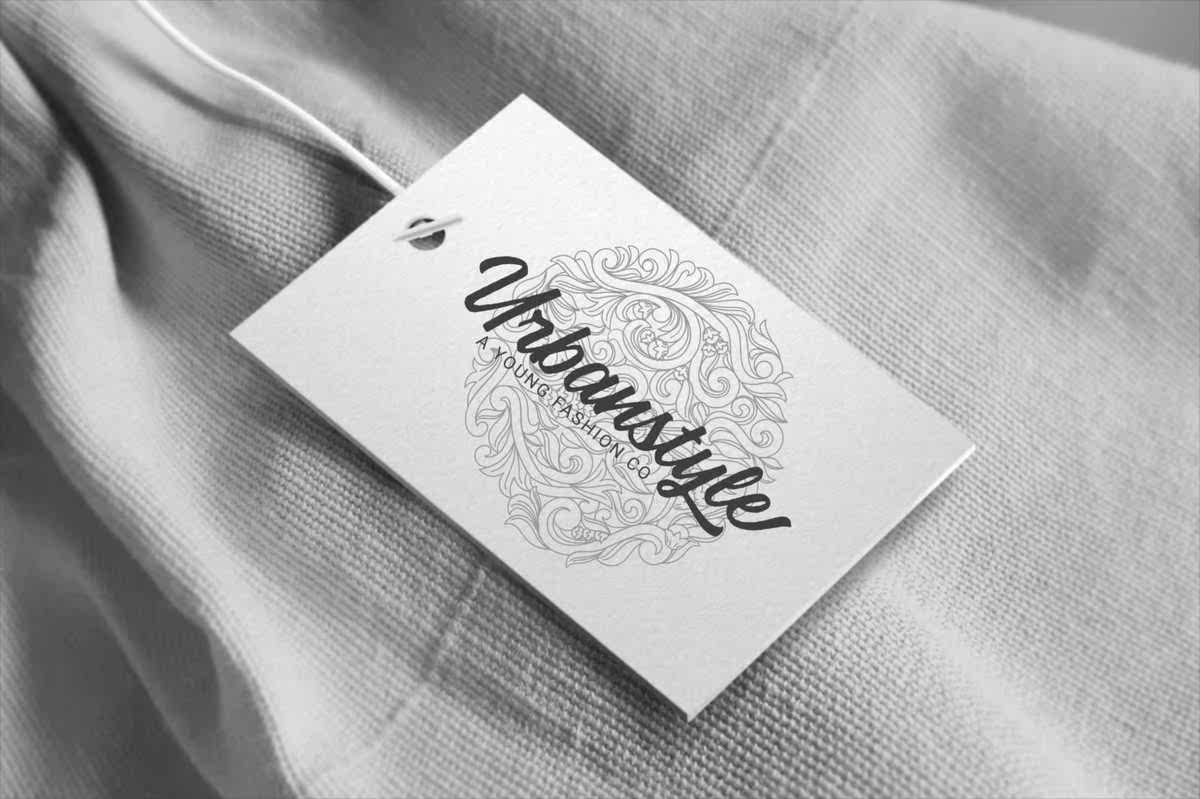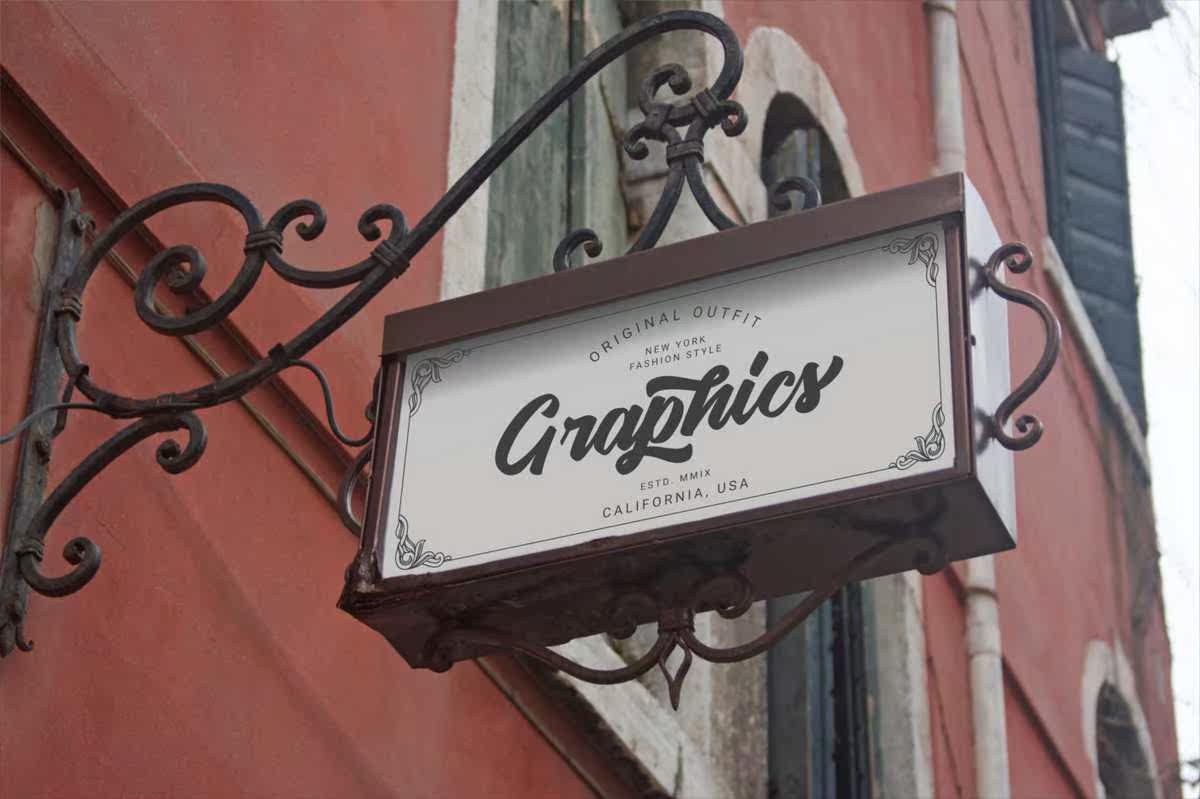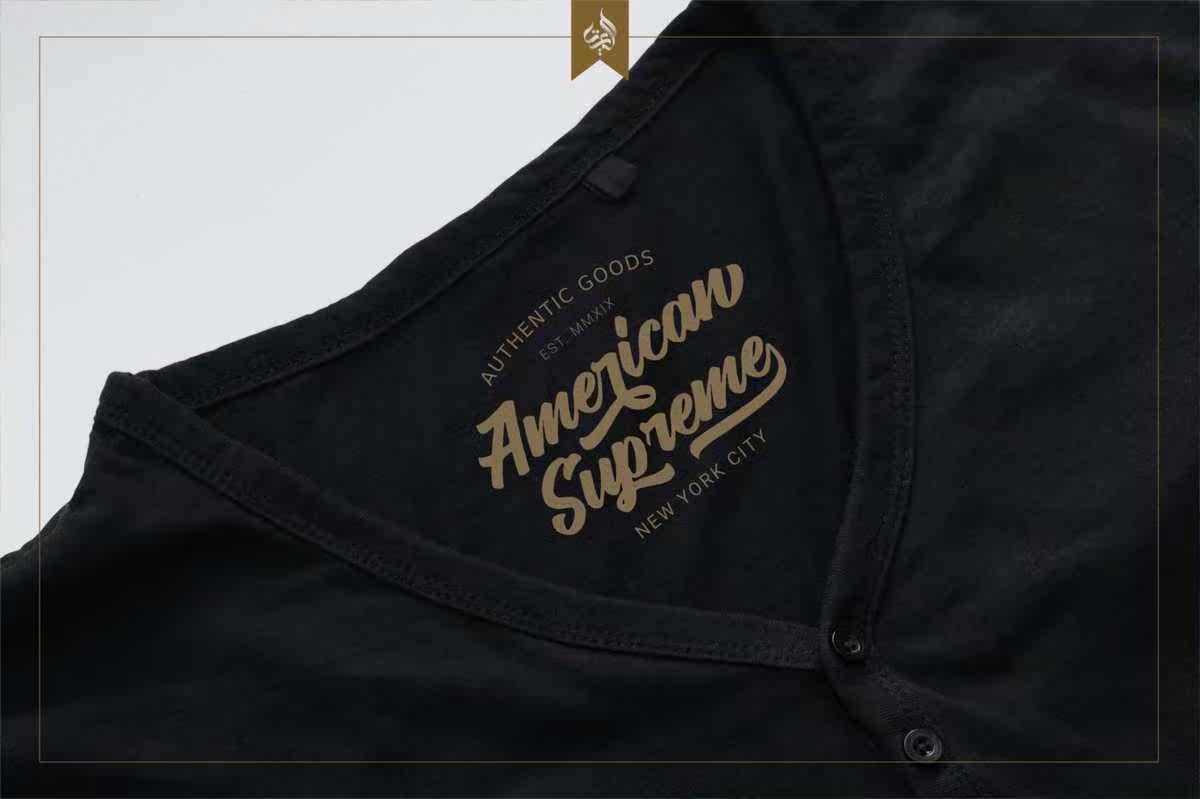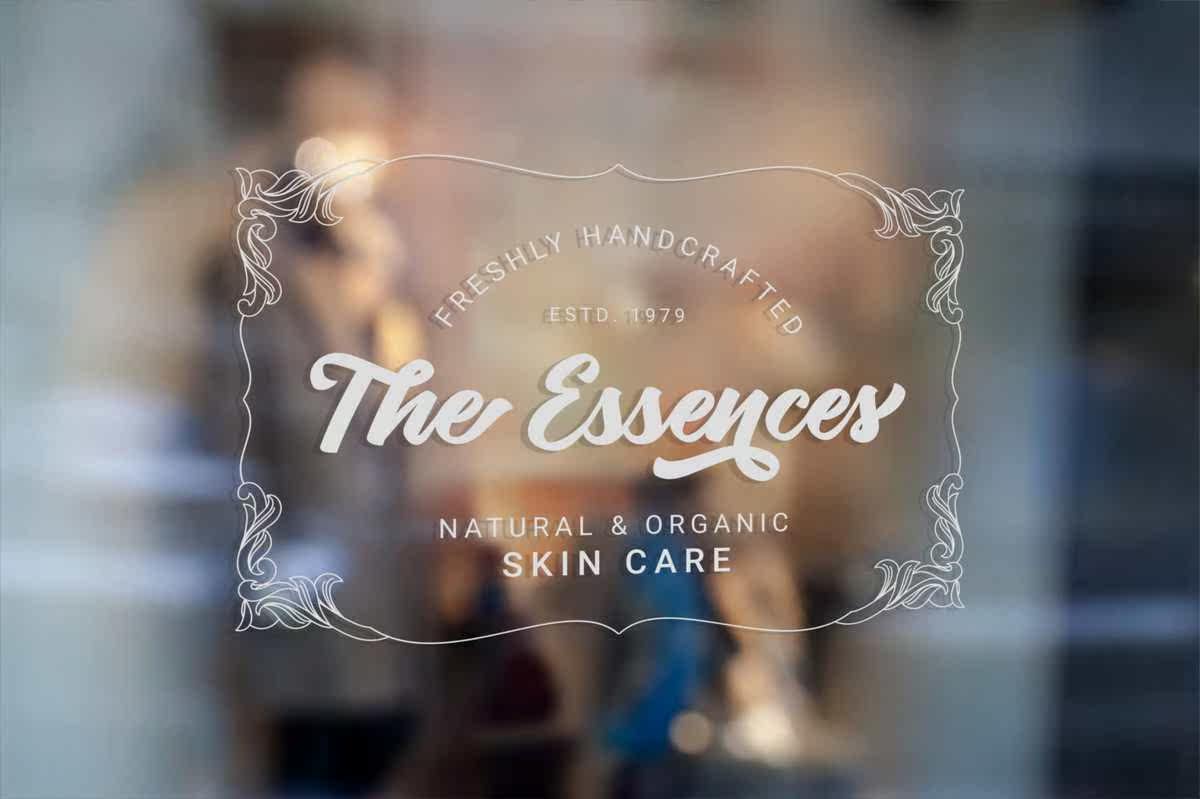
Vigrandisa是一款手感极佳的手写字体。使用它来完成任何设计项目。具有6种风格、规则、规则、粗体、粗体、粗体和粗体。高达5级交替。Opentype、swash、连字、多语言支持(WesterneuropeanCharacters)和以下语言的工作:英语、法语、意大利语、葡萄牙语、德语、瑞典语、,诺维根、丹麦、荷兰、芬兰、印度尼西亚、菲律宾、马来。)PUA编码,易于使用。不适用于特殊软件。Vigrandisa使用无触感的令人震惊的手写字体。使用ITT LoadDauniqueCharmToany设计项目。具有6种风格、常规、规则、规则、规则、粗体、粗体和粗体。最多5级交替。开放式、swash、连字、多语言支持,(WesterneuropeanCharacters并使用以下语言工作:英语、法语、意大利语、葡萄牙语、德语、瑞典语、挪威语、丹麦语、荷兰语、芬兰语、印度尼西亚语、菲律宾语、马来语。)PUAENCODE,易于使用。不适用于特殊软件。